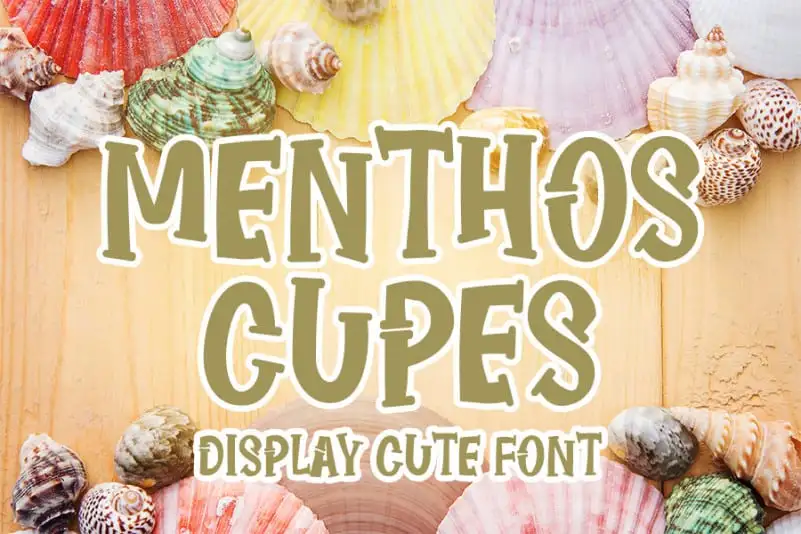
MENTHOS CUPES Display Font – Download Grátis
A MENTHOS CUPES Display Font é uma opção ideal para designers que buscam equilíbrio entre elegância clássica e modernidade contemporânea. Este tipo de fonte mantém as influências do desenho a mão, garantindo um estilo sofisticado, enquanto se mantém atual e inovador. Suas possibilidades variadas tornam-a uma escolha versátil para diversas ideias criativas, desde assinaturas e títulos até materiais de correspondência. Com esta fonte à disposição, você pode explorar um vasto leque de opções de design, adaptando suas criações para diversos usos. Ideal tanto para designers profissionais quanto para entusiastas do design, a MENTHOS CUPES Display Font é uma escolha inteligente para quem valoriza tanto o encanto clássico quanto as tendências atuais.